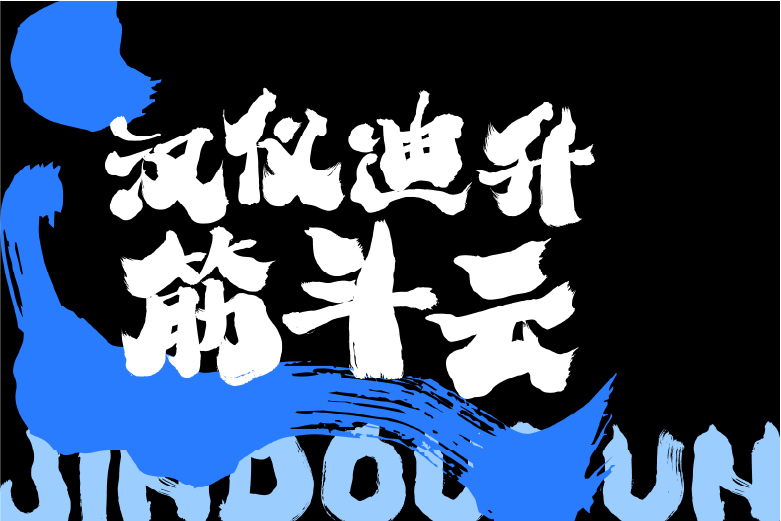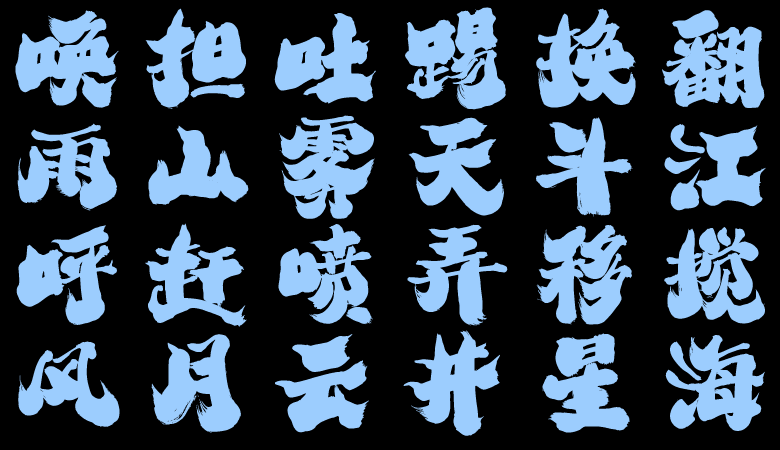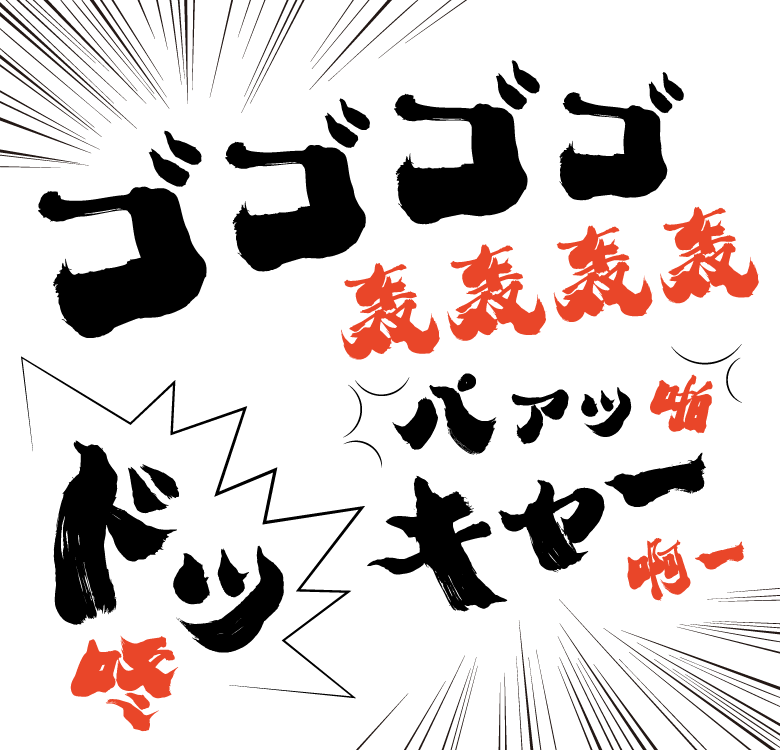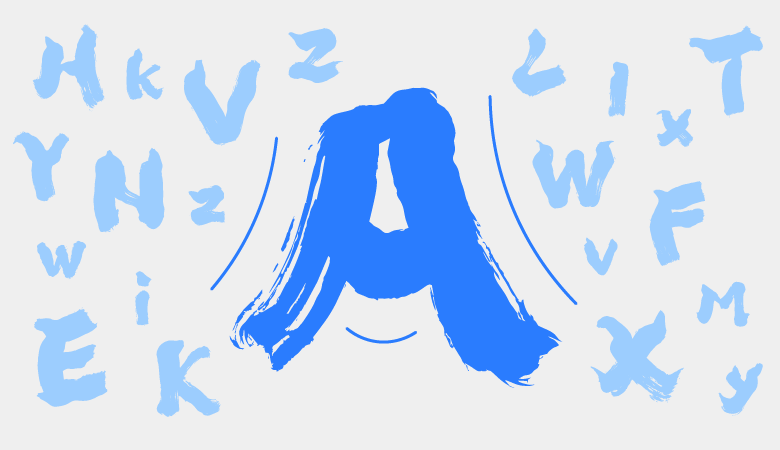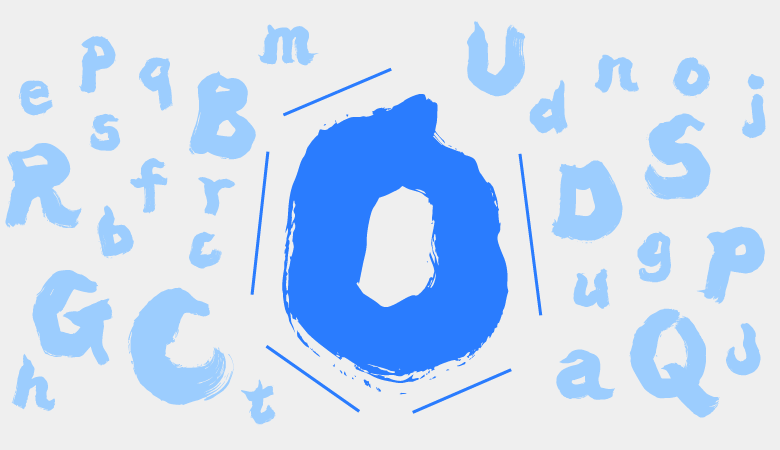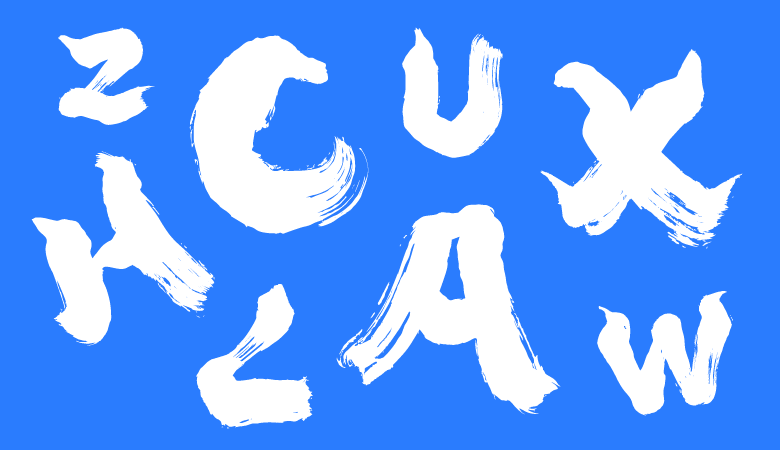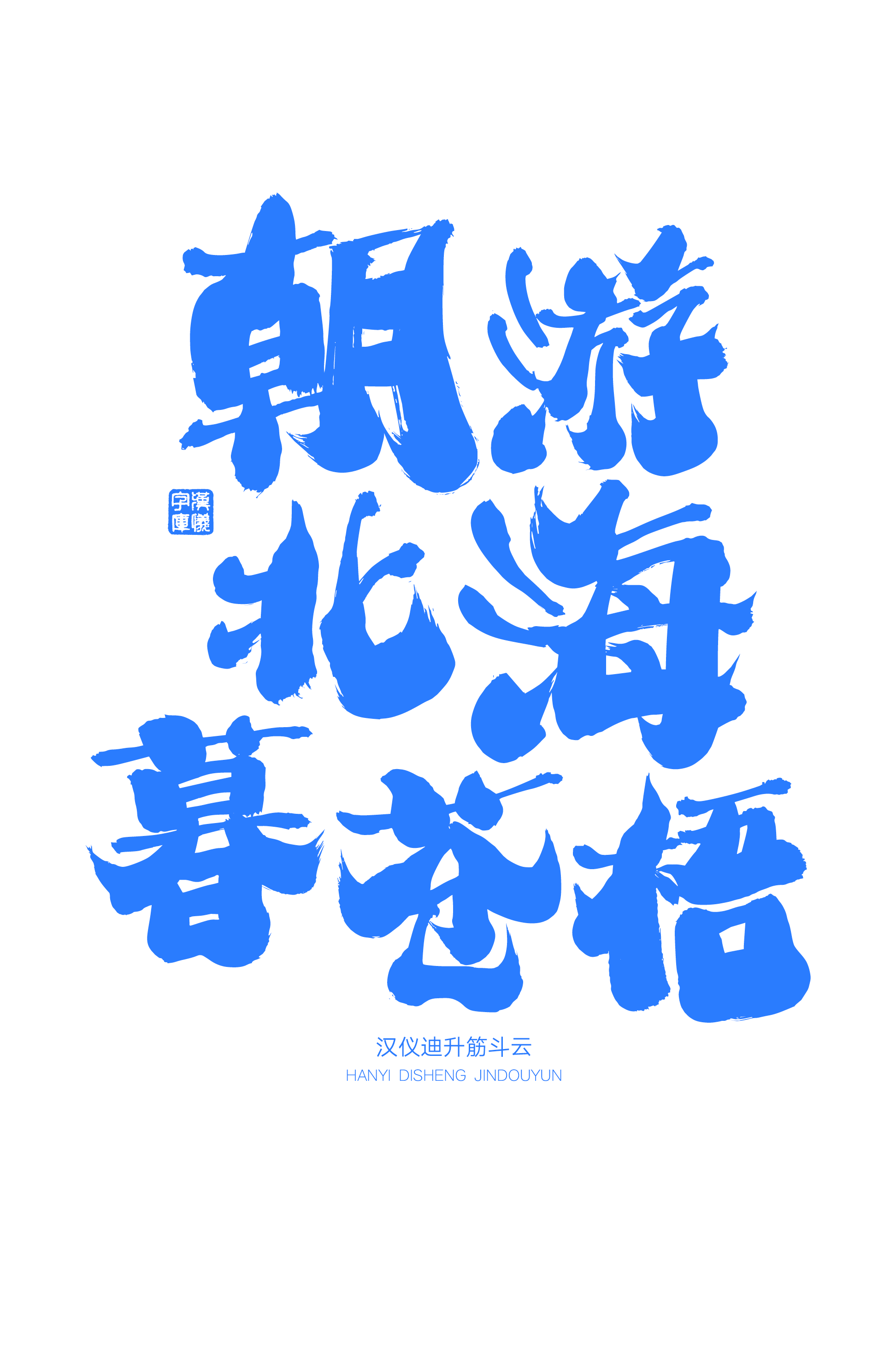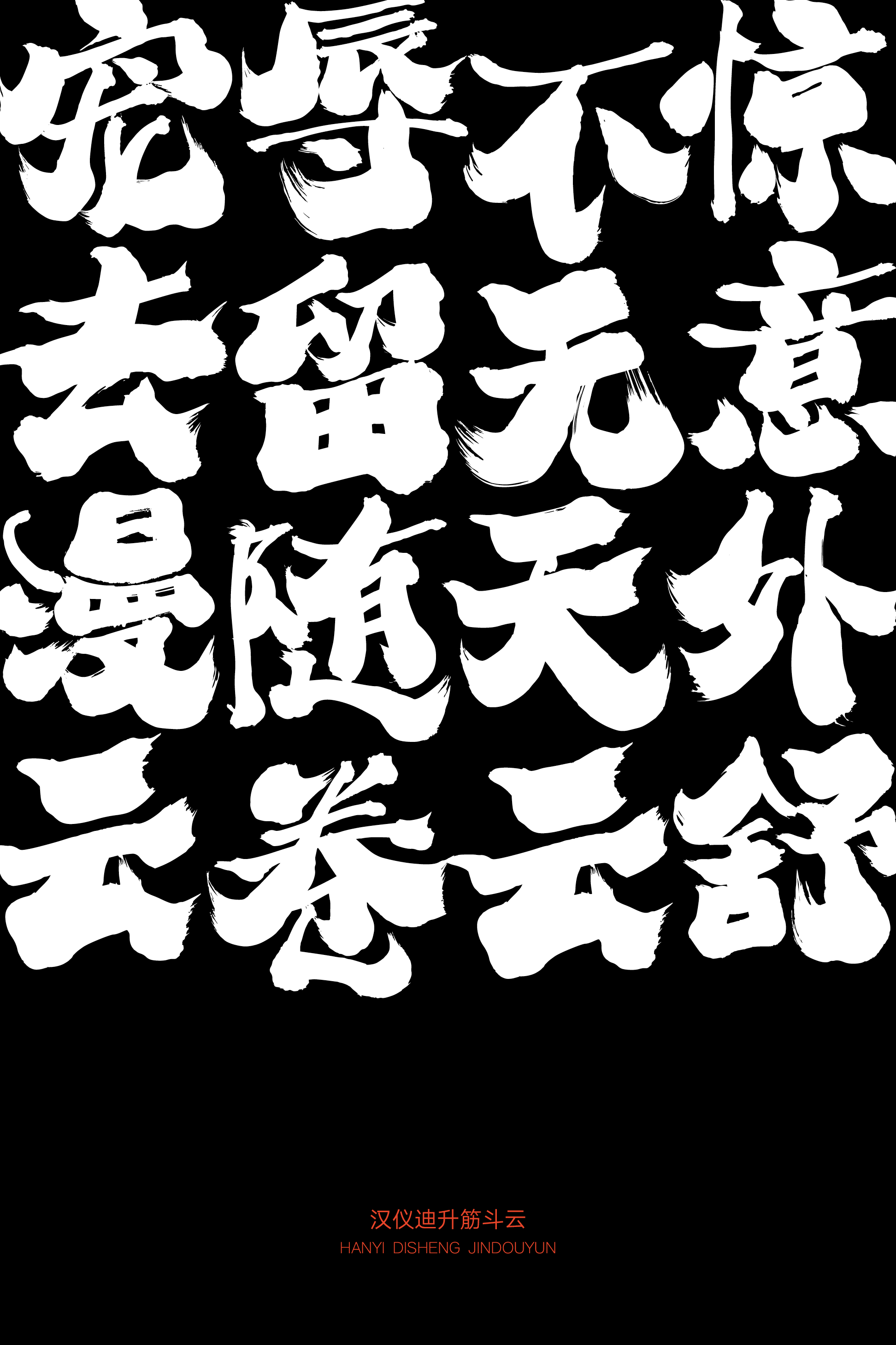
一款自在逍遥,蓄筋斗云之动势的字体
书写字体
传统 / 国风 / 书写 / 潇洒
汉仪迪升筋斗云是由青年艺术家、汉仪字库签约作者迪升创作的一款气质潇洒的国风书写字体,无拘无束,自在逍遥,静中带动,蓄筋斗云之动势。适合作为广告海报、游戏动漫、影视娱乐、产品包装等多种场景的标题字来使用。
迪升,仗笔行走现代江湖的独立手写人、艺术创作者。白纸黑字、一笔一画,用笔墨对话传统与现代,用光阴书写热爱与坚持。
为了突破传统的边界,进一步增强现代装饰感,作者迪升在书写这款字体时选择了动物毛的圆头水彩笔,带来与传统书法截然不同的绘画感。
这款字体中宫紧凑,重心偏高,底部放松而向上略微收紧,蓄势待发。
这款字体笔画放达洒脱,细节处尽显手书之奔放,行笔间尽显变化之丰富。
顿笔显遒劲,可谓“一筋斗就有十万八千里路”。
收笔显逍遥,手写飞白有如腾云驾雾。
汉仪迪升筋斗云的书写风格飘逸而不失克制,视觉上呈现的力度恰如其分,排版效果均衡舒适,也适用于竖排文字。
这款字体同样覆盖了日文假名,可以满足更为广泛的使用场景。
这款字体的西文字体设计保留了顿笔和笔画的飞白效果,赋予拉丁字母国风书写之美,挥洒自如,中西文搭配和谐。
顿笔破直为曲,圆中取方。
笔画飞白添一分飘逸仙气。